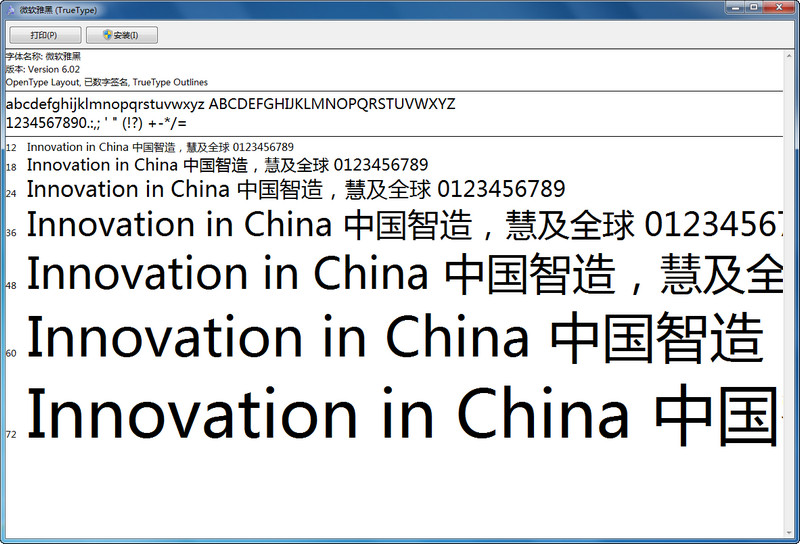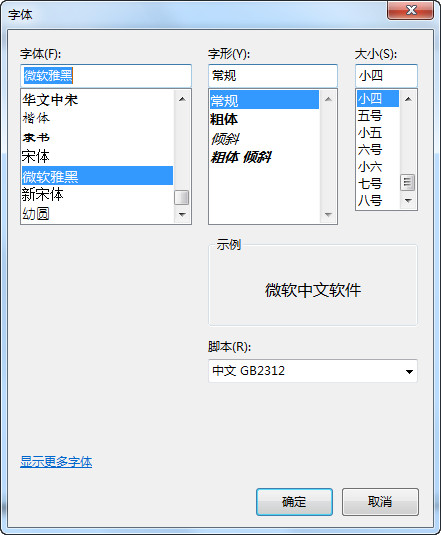
微軟雅黑是美國(guó)微軟公司委托中國(guó)北大方正電子有限公司設(shè)計(jì)的一款全面支持ClearType技術(shù)的字體。Monotype公司負(fù)責(zé)字體Hinting工作。它屬于OpenType類(lèi)型,文件名是MSYH.TTF,字體設(shè)計(jì)上屬于無(wú)襯線字體和黑體。這種字體每個(gè)字的造價(jià)成本在100美元左右。該字體家族還包括“微軟雅黑Bold”(粗體),文件名為MSYHBD.TTF。這個(gè)粗體不是單純的將普通字符加粗,而是在具體筆畫(huà)上分別進(jìn)行處理,因此是獨(dú)立的一個(gè)字體。微軟雅黑隨簡(jiǎn)體中文版Windows Vista一起發(fā)布,是Windows Vista默認(rèn)字體。另外,Microsoft office 2007簡(jiǎn)體中文版也附帶這個(gè)字體。
在涵蓋的字庫(kù)上,微軟雅黑支持GBK字符集,包含了Unicode的所有 20902個(gè)中文字符以及中國(guó)國(guó)家標(biāo)準(zhǔn)化組織添加的大約 80個(gè)中文字符,還包含了Big5的繁體中文字符和GB2312中的簡(jiǎn)體中文字符。
微軟雅黑體是一款全新的支持 ClearType技術(shù)的中文界面顯示字體浮出水面,這就是微軟雅黑體。
這款字體是一種全新的無(wú)襯線黑體,它的字形略呈扁方而飽滿,筆畫(huà)簡(jiǎn)潔而舒展,易于閱讀。這款字體在 ClearType 技術(shù)下的清新和優(yōu)美著實(shí)給人留下了深刻的印象。同時(shí),微軟方面也為這種新型字體付出了昂貴的代價(jià)。“這種字體每個(gè)字的造價(jià)成本在100美元左右,據(jù)不完全統(tǒng)計(jì),我國(guó)各字典、詞海收錄有2萬(wàn)多個(gè)漢字”。
1. 單獨(dú)設(shè)計(jì)的粗體。
2. 顯示品質(zhì)優(yōu)異的斜體。
3. 更清晰的小號(hào)字顯示。
4. 對(duì)于最常用的字號(hào)。
5. 更優(yōu)美而現(xiàn)代的字形設(shè)計(jì)。